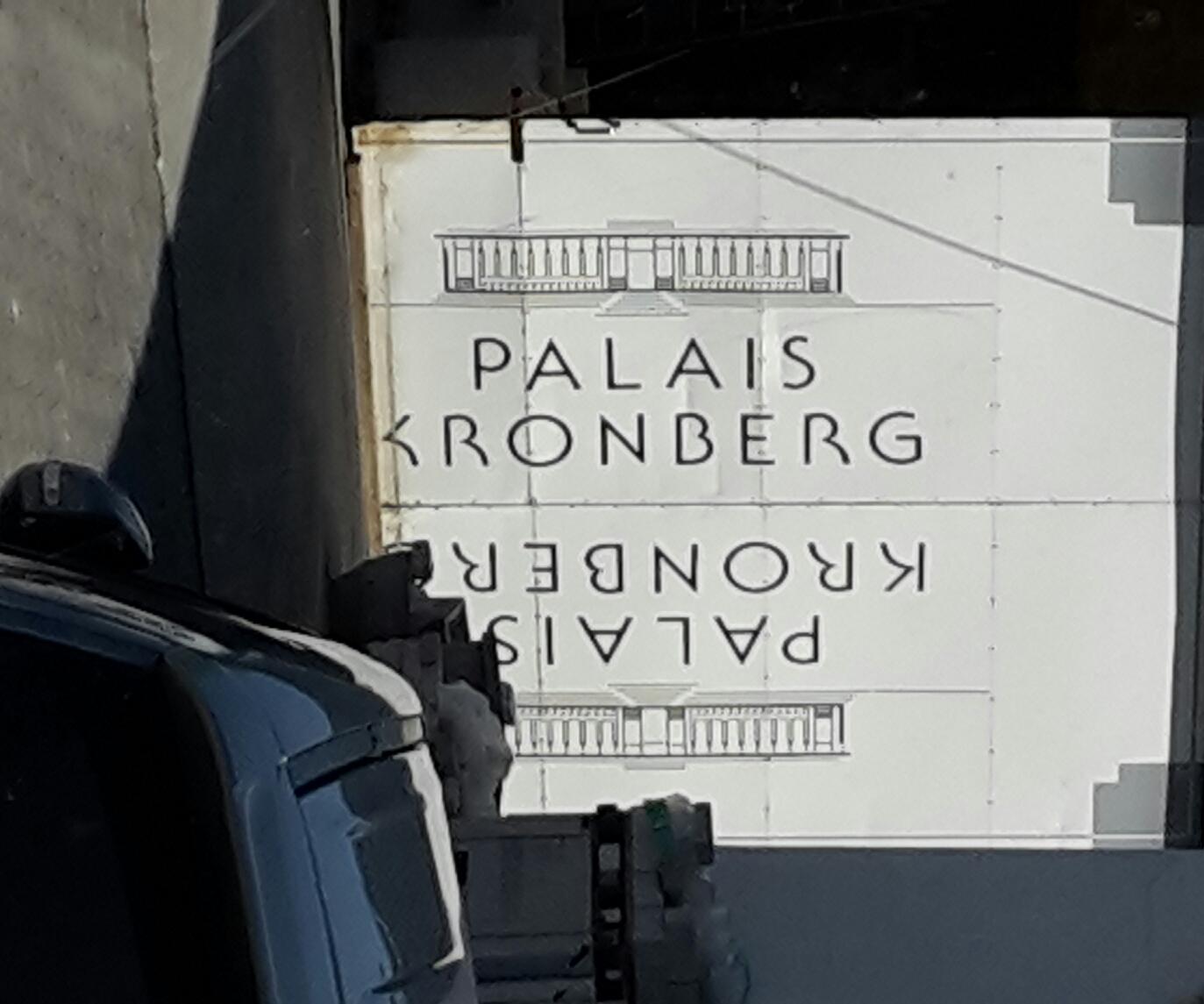
suche die Schrift der Plakatwand PALAIS KRONBERG
Hallo. Bin neu hier und habe diese Schrift an einem Hallentor in Steinau an der Straße gesehen. Ich finde sie ist eine perfekte Kombination aus klassisch und modern. Vielleicht weiß jemand wie sie heißt...